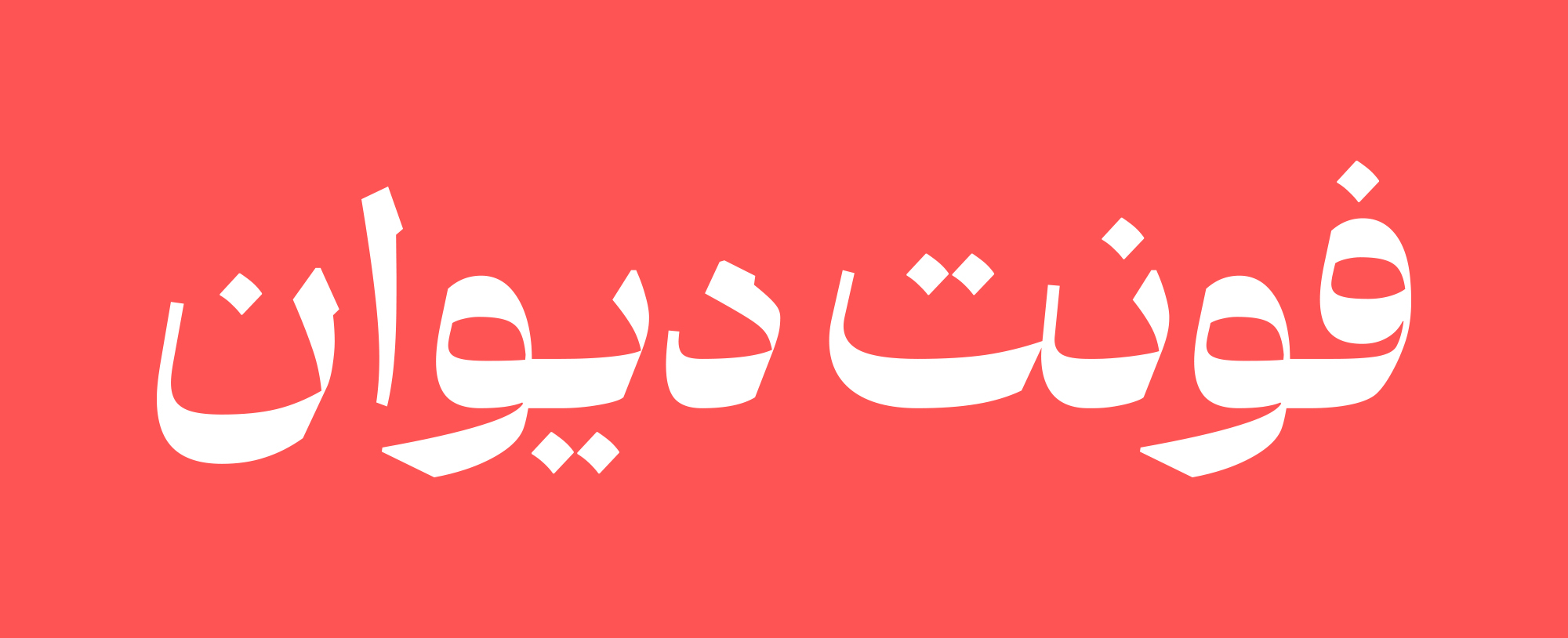
فونت دیوان
فونت دیوان با وقار و اصیل است و با روحیهٔ قاطع و متین خود، نقطه تلاقی بین گذشته باشکوه و حالِ پُرظرافت است.
این فونت تک وزن نمایشی با کنتراست بالا، بازآفرینی جسورانه‌ای از روح خط ثلث است که با ظرافت، از ساختار خط نسخ پیروی می‌کند.
فونت دیوان با پشتیبانی از زبان‌های فارسی، تورکی، عربی، اردو، کوردی و جاوی، گزینه‌ای بی‌همتا برای طراحان خوش‌ذوق در پروژه‌های فرهنگی، هنری، ادبی و سنتی است و در طراحی تیترها، عناوین، متن‌های کوتاه تبلیغاتی، پوستر، کاور، جلد کتاب و... کاربرد دارد.
در فونت دیوان هویت خط، با نوآوری معاصر دست در دست هم داده‌اند تا نوشتار را به یک اثر هنری بدل کنند.
ترکیبات، جایگزین‌ها و لگیچرها
فونت دیوان در استفاده